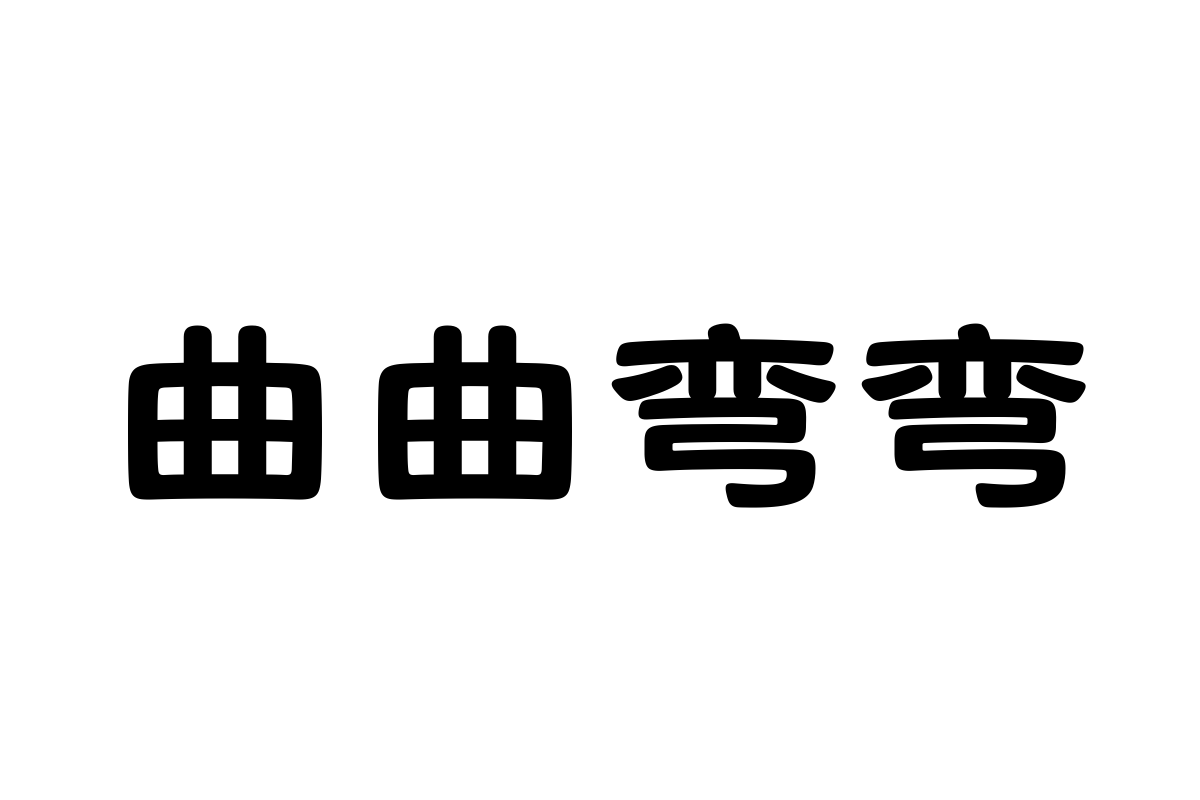
汉仪玉筋隶85是一款具有现代感的中文字体,它采用了简洁而流畅的设计,使得文字看起来既优雅又有力。这款字体的特点是笔画粗细均匀,线条清晰,给人一种干净利落的感觉。同时,它的字形结构紧凑,使得整个字体看起来更加饱满,富有层次感。
在设计上,汉仪玉筋隶85注重细节的处理,每个笔画都经过精心雕琢,使得整体效果更加完美。无论是用于标题、正文还是装饰性的文字,这款字体都能展现出其独特的魅力。
总的来说,汉仪玉筋隶85是一款非常适合现代设计需求的中文字体,无论是用于印刷品、网站还是其他媒体,都能展现出其独特的美感和实用性。